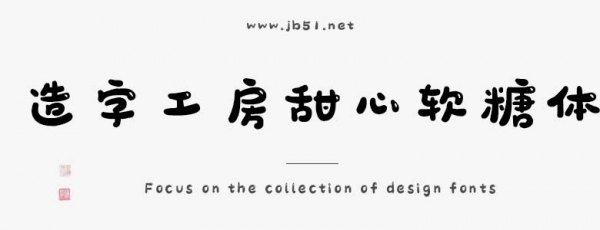
造字工房甜心軟糖體由上首造字字庫出品的字體,充滿童趣與甜蜜氣息,字形圓潤飽滿,筆畫如軟糖般Q彈可愛,仿佛散發(fā)著糖果的香甜。適合應(yīng)用于平面宣傳設(shè)計、網(wǎng)頁設(shè)計,書法字帖等領(lǐng)域,需要的朋友可以前來本站下載。
造字工房甜心軟糖體是一款充滿童趣與甜蜜氣息的創(chuàng)意字體。字形圓潤飽滿,筆畫如軟糖般Q彈可愛,仿佛散發(fā)著糖果的香甜。呈現(xiàn)出活潑跳躍的動感,猶如孩童歡快的步伐。字重適中,兼具易讀性與軟萌氣質(zhì),整體設(shè)計充滿活潑跳躍的動感,適合用于傳遞輕松愉悅的氛圍。本字體為簡體字庫,采用OpenType/CID格式,Adobe-GB1-5編碼?;谥腥A人民共和國GB2312-80字符集標準,另按需添加101個漢字。共收容字數(shù)6864CJK漢字,ASCII常用字符100個。